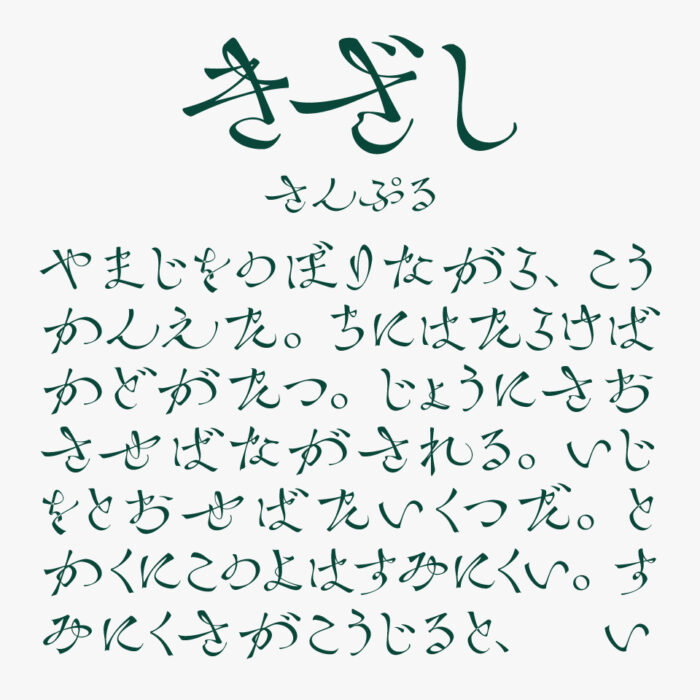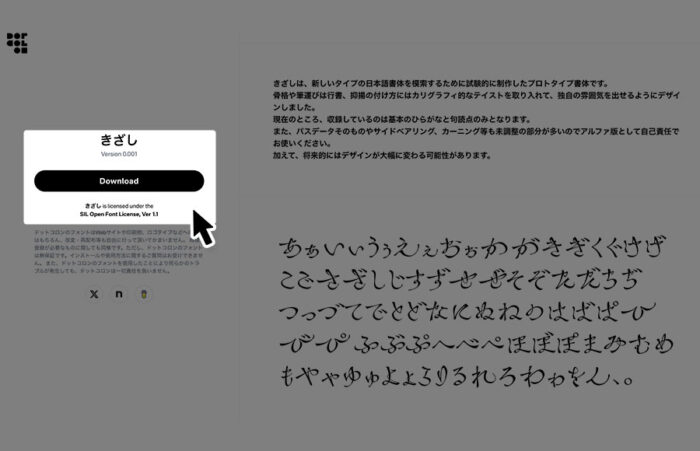
繊細な筆使いが印象的な、行書体風の流れるような文字やのような抑揚が特徴的な筆文字フォントです。
細く長い筆跡が連なり、まるで手紙や詩のような美しさを持っている上品で静かなデザインなフォントです。
和風のデザインや、歴史・文学を感じさせるコンテンツにぴったりです。
収録文字は、現在はひらがなのみ収録されています。アルファ版としてリリースされているフォントなので、今後のアップデートで文字が追加される可能性があるようです。